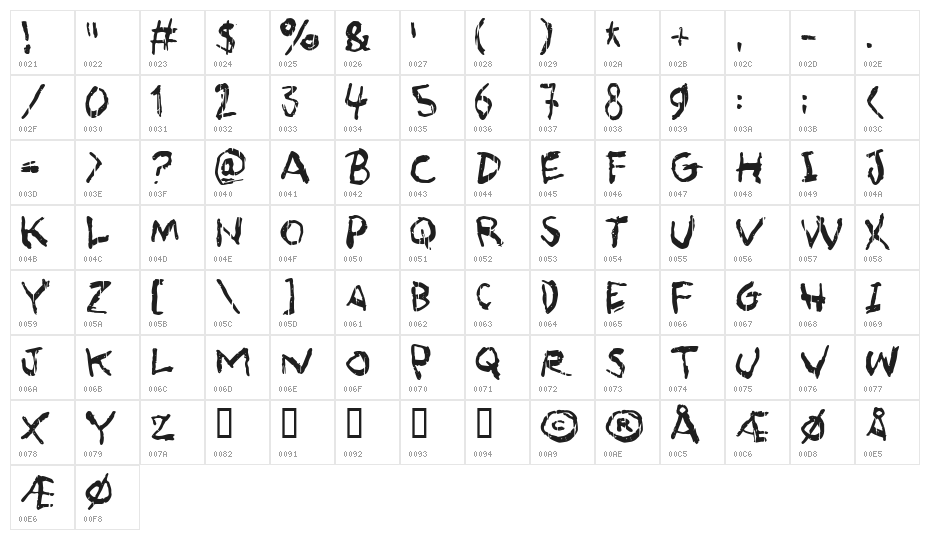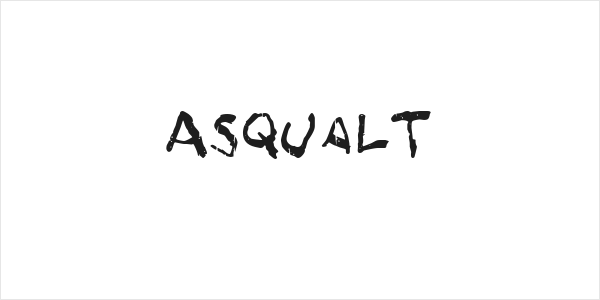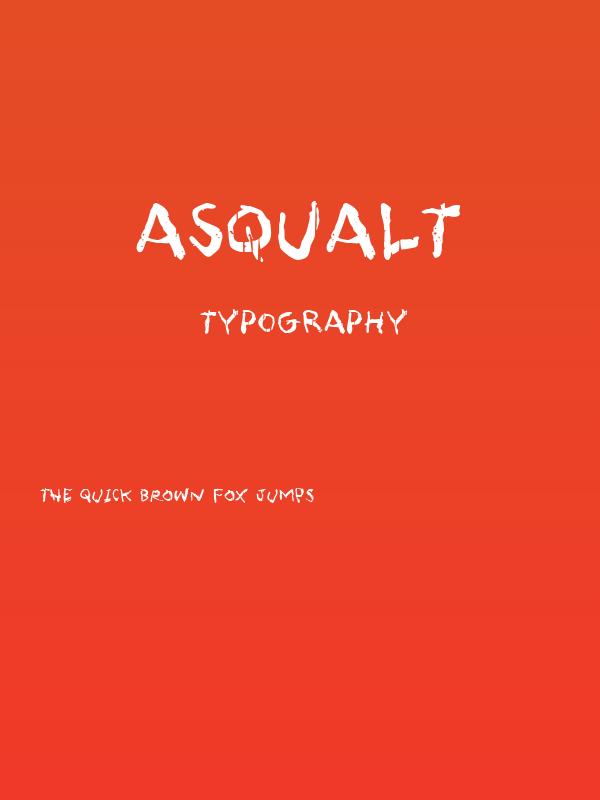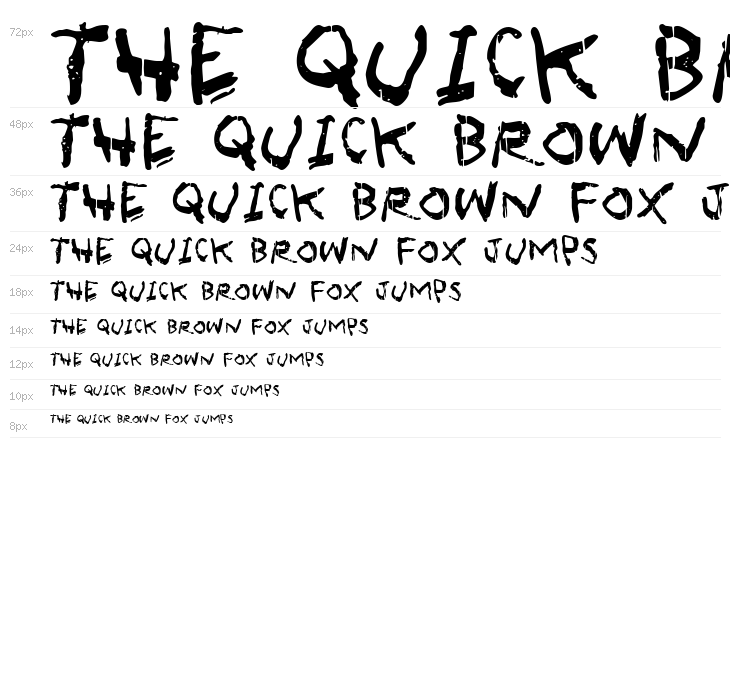
Asqualt Font
| Progetti proposti | Ideal for projects requiring a bold statement, such as posters, album covers, graffiti art, and edgy branding materials. |